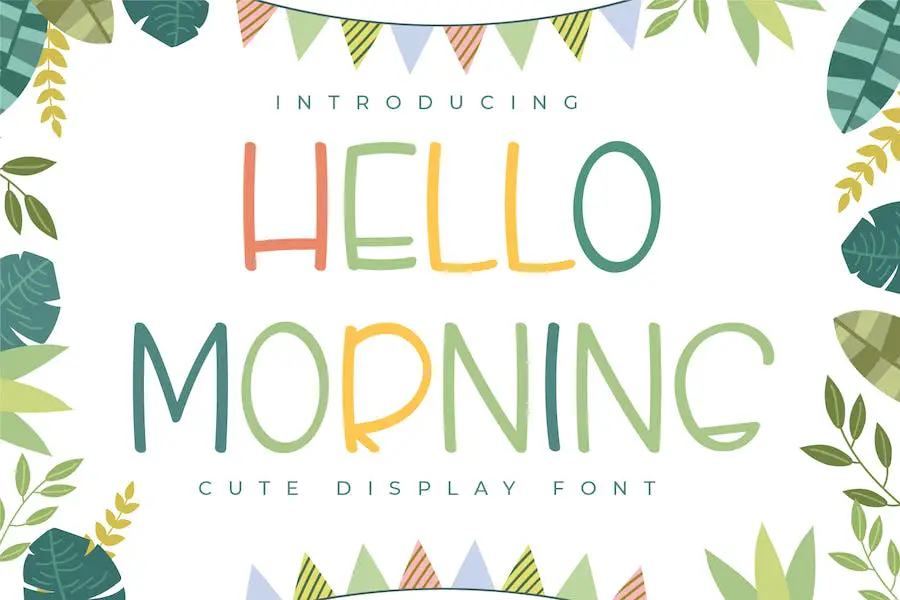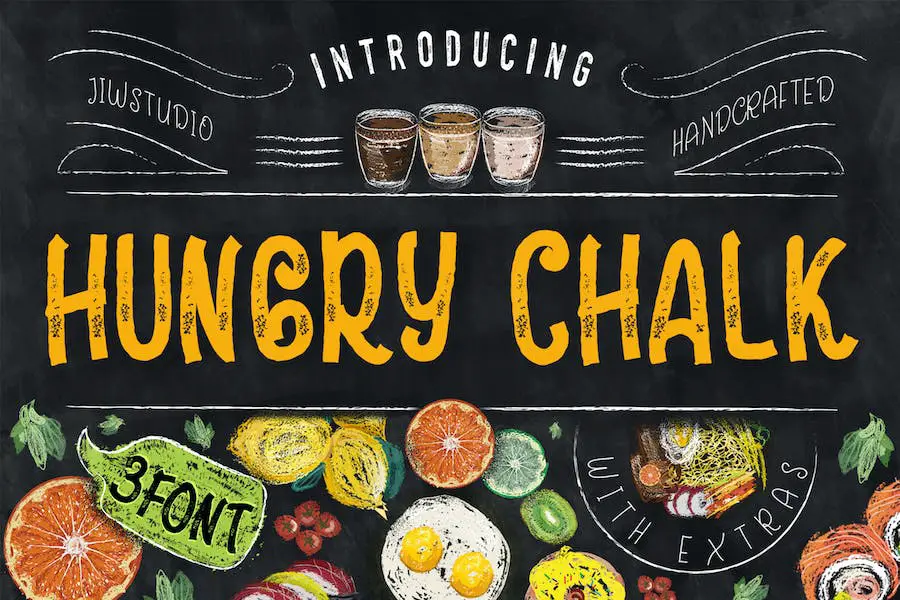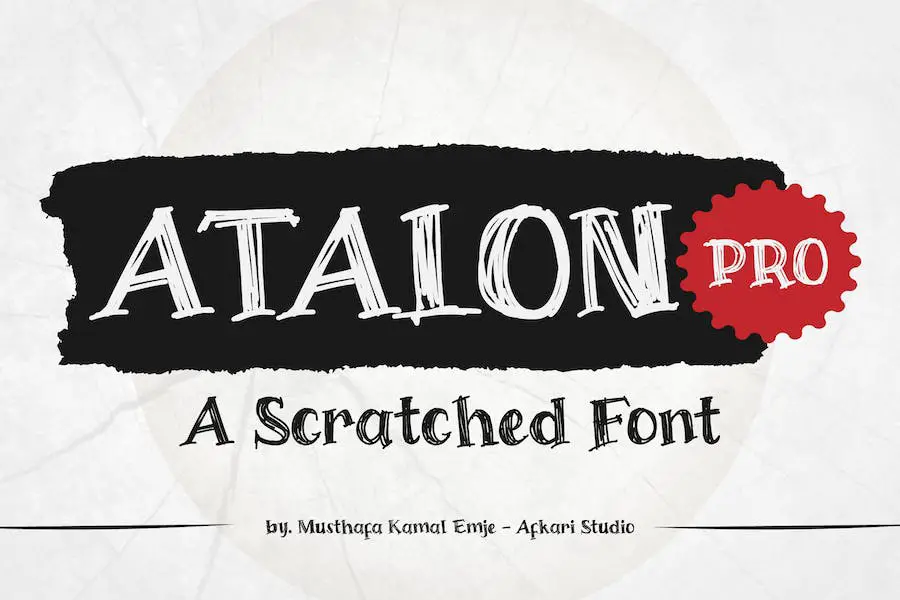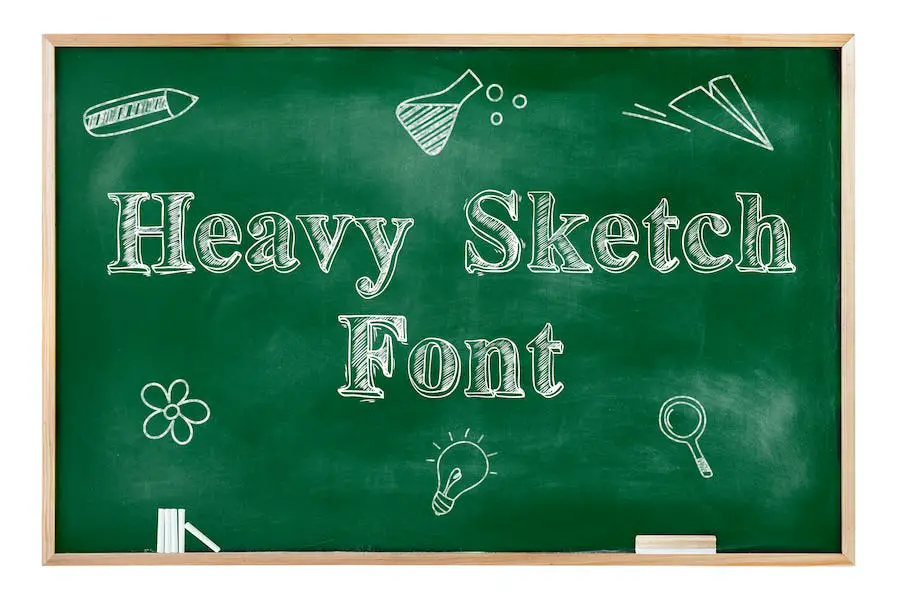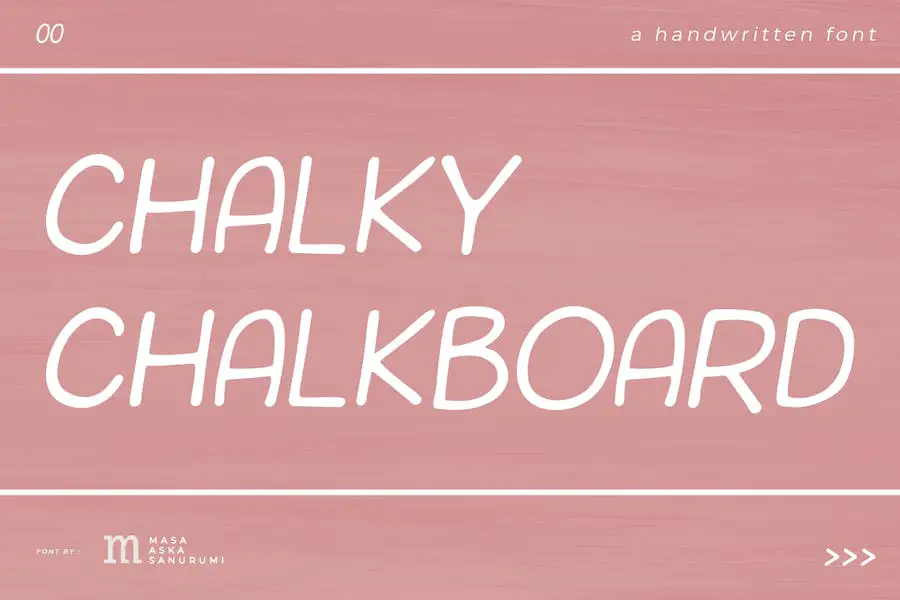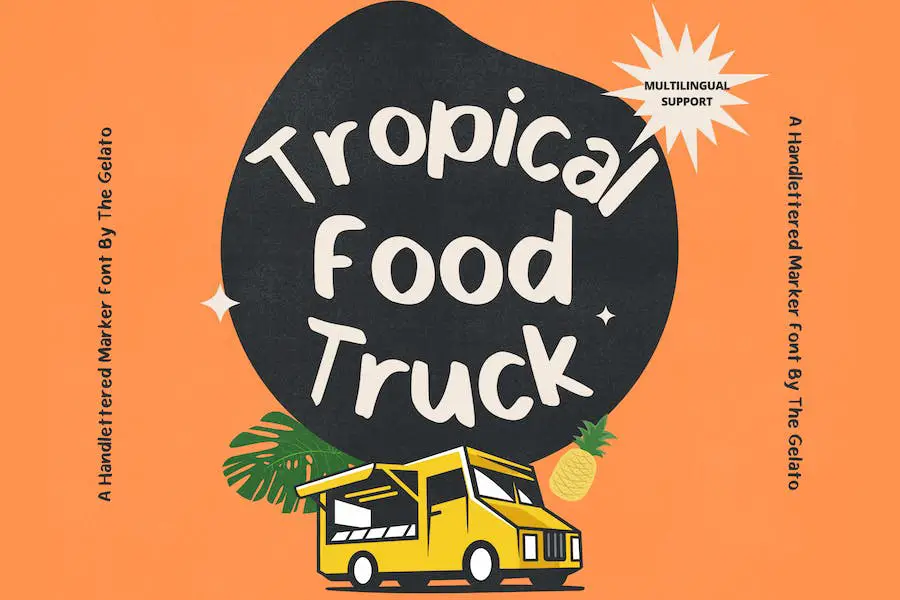
Cele mai bune 31 de fonturi Chalkboard 2023 (gratuit și premium)
Publicat: 2023-09-06Sunteți un designer grafic în căutarea fontului perfect pentru a vă ridica proiectele? Nu căutați mai departe decât lista noastră cu cele mai bune 31 de fonturi de tablă pentru 2023! Acum, s-ar putea să vă întrebați, de ce fonturi de tablă?
Ei bine, aceste fonturi adaugă o notă unică și nostalgică oricărui design, făcându-le perfecte pentru a crea imagini atrăgătoare care ies în evidență. Dar, având atâtea opțiuni, poate fi copleșitor să restrângi opțiunile.
Acolo intrăm noi! Am pregătit o listă cu cele mai bune fonturi de tablă disponibile, astfel încât să puteți economisi timp și să vă concentrați pe ceea ce faceți cel mai bine – proiectarea! Așadar, haideți să ne scufundăm și să explorăm împreună lumea fonturilor de tablă!
În acest articol, vom prezenta primele 31 de fonturi de tablă care vă vor duce cu siguranță proiectele de design la nivelul următor. Am făcut cercetările și am ales aceste fonturi pe baza popularității, versatilității și atractivității lor vizuale.
Nu numai că vă vom prezenta aceste fonturi, dar vă vom oferi și câteva statistici și fapte cheie despre fiecare. Indiferent dacă proiectați un poster, un logo, un site web sau orice alt proiect creativ, aceste fonturi pot adăuga o notă de farmec, creativitate și capriciu.
Acum, înainte de a trece la compilația celor mai bune fonturi de tablă, haideți să discutăm rapid despre ce face aceste fonturi atât de speciale. Fonturile cu tablă aduc un sentiment de nostalgie, deoarece seamănă cu stilul scris de mână întâlnit adesea pe tablele de clasă.
Aspectul lor unic și rustic poate evoca sentimente de căldură și familiaritate, făcându-le perfecte pentru o varietate de proiecte de design.
Așadar, dacă sunteți gata să descoperiți cele mai bune 31 de fonturi de tablă pentru 2023, haideți să ne aprofundăm și să găsim fontul perfect pentru a vă îmbunătăți design-urile!
Cele mai bune fonturi Premium Chalkboard
Doriți să vă ridicați proiectele de design grafic cu o notă de farmec nostalgic? Nu căutați mai departe decât lista noastră organizată cu cele mai bune fonturi premium pentru tablă. Aceste fonturi versatile pot îmbunătăți designul oricărui proiect, de la invitații la semnalizare.
Deci, de ce să aștepți? Scufundați-vă și descoperiți fontul perfect pentru a adăuga o notă de eleganță scrisă de mână creațiilor dvs.
Tablă de cretă
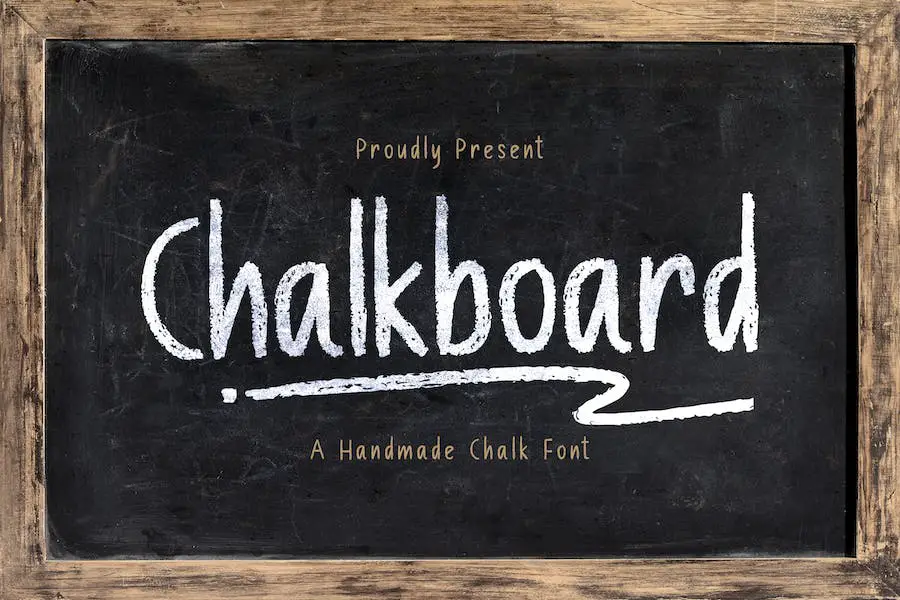
Chalk Board este un font de pensulă texturat realizat manual, conceput pentru a surprinde esența cretei. Cu scenariul său unic, aduce o senzație serioasă și sinceră oricărui proiect de design. Indiferent dacă lucrați la o felicitare, un semn sau un logo, acest font cu siguranță vă va ridica designul cu stilul său autentic inspirat de cretă.
Textura și liniile de pensulă ale Chalk Board îl fac să iasă în evidență față de alte fonturi. Adaugă o notă de personalitate și farmec design-urilor tale, dându-le o senzație autentică și realizată manual.
Ușoarele imperfecțiuni ale literelor imită denivelările cretei de pe o tablă, adăugând o notă jucăușă și nostalgică.
Tablă groasă
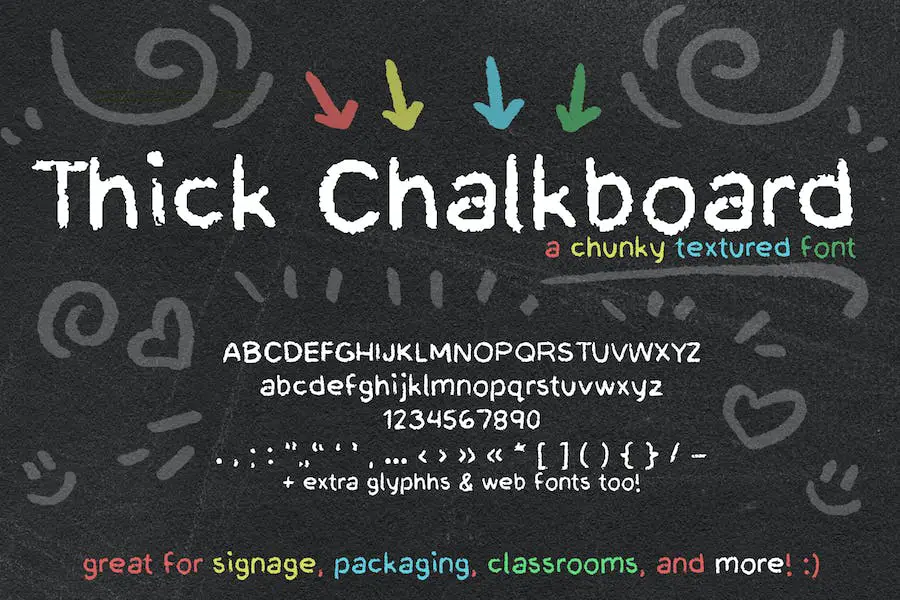
Thick Chalkboard este un font de cretă scris de mână încântător care aduce o notă de fantezie proiectelor tale de design.
Conceput pentru creativitate, Thick Chalkboard este un font versatil care poate fi folosit pe diverse platforme.
Cretă manuală
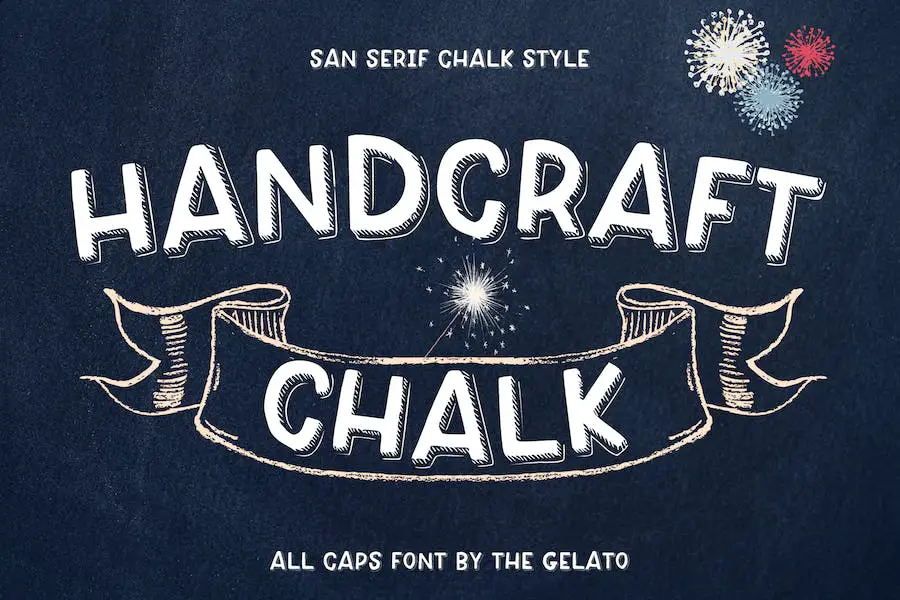
Handcraft Chalk este un font încântător care imită farmecul și simplitatea literelor scrise de mână cu cretă. Acest font cu majuscule este perfect pentru designerii grafici care doresc să adauge o notă de nostalgie proiectelor lor.
Datorită versatilității sale, Handcraft Chalk poate fi folosit ca font de tablă, font de cretă scris de mână sau chiar ca font de cretă pentru meniu.
Frumusețea cretei artizanale constă în stilul său unic San Serif. Acest lucru oferă design-urilor dvs. un aspect curat și modern, păstrând în același timp acea senzație clasică de tablă.
Tuck Shop
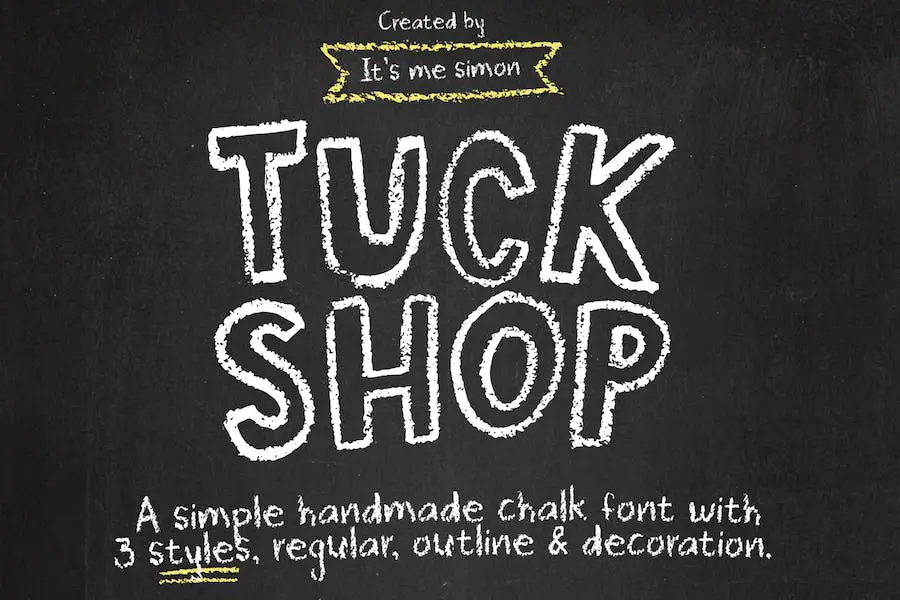
Tuck Shop este un font care te duce înapoi la școală și la panourile de anunț fermecătoare din afara cafenelelor. Perfect pentru cărțile și postere pentru copii, această fontă distractivă și casual poate îmbunătăți orice proiect care necesită un stil cretă.
Pe lângă fontul în sine, Tuck Shop oferă și o colecție de 77 de ornamente, de la stele la bule de vorbire, oferindu-vă o multitudine de opțiuni pentru a adăuga această notă suplimentară design-urilor dvs.
Ceea ce diferențiază Tuck Shop este afișajul său detaliat și personalitatea sa copilărească și naivă. Desenat manual cu cretă reală pe o tablă de ardezie naturală, acest font poate părea dur și neîngrijit, dar asta este ceea ce adaugă farmecul său irezistibil.